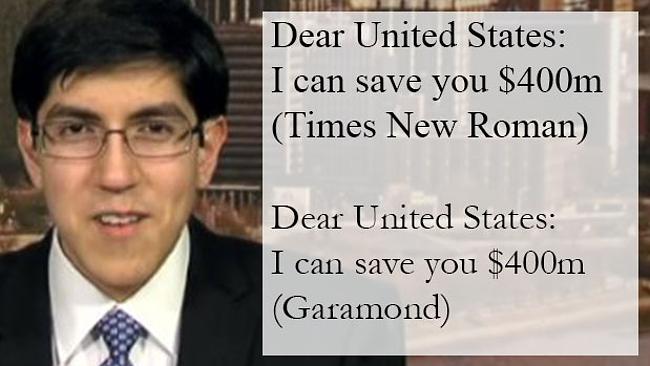
Cậu bé 14 tuổi từng muốn "đổi font chữ” để tiết kiệm 400 triệu USD cho Mỹ gây chấn động thế giới giờ ra sao?
Năm 2014, thông tin cậu bé Suvir Mirchandani, 14 tuổi muốn hiến kế cho chính phủ Mỹ thay đổi font chữ để giúp tiết kiệm hàng trăm triệu USD tiền in ấn mỗi năm khiến dư luận ở quốc gia này “dậy sóng”.
Theo Suvir Mirchandani, tính theo thể tích, mực còn đắt gấp đôi nước hoa Pháp. Và trên thực tế, sự tính toán này hoàn toàn chính xác. Cụ thể, mỗi ounce (30 ml) nước hoa Chanel No.5 có giá 38 USD, với cùng thể tích đó lượng mực in chạy cho máy Hewlett Packard ở Mỹ có thể có giá lên đến 75 USD.
Cậu bé Suvir Mirchandani
Cậu bé muốn thay đổi font chữ để giúp tiết kiệm tiền in ấn cho Mỹ. (Ảnh: CNN.)
Cậu bé đã sử dụng cả phương pháp vật lý và phần mềm để chứng minh cách dùng font chữ hiện nay tốn mực in khủng khiếp như thế nào.
Cụ thể, Suvir thử nghiệm viết những chữ cái bằng 4 kiểu font chữ Garamond, Times New Roman, Century Gothic và Comic Sans và sau đó sử dụng công cụ APFill® Ink Coverage Software bản thương mại để đo lường lượng mực in. Kết quả cho thấy, nếu sử dụng Garamond, một loại font có nét mảnh mai hơn, thì hàng năm trường học của cậu bé có thể tiết kiệm được 24% lượng mực in, tương đương với số tiền 21.000 USD.
Và nếu font chữ này được sử dụng rộng rãi ở toàn nước Mỹ thì số tiền mực in có thể tiết kiệm lên tới khoảng 400 trăm triệu USD mỗi năm.
Nếu thay đổi font chữ, số tiền mực in có thể tiết kiệm lên tới khoảng 400 trăm triệu USD mỗi năm
Mặc dù rất tiềm năng nhưng người ta không thể áp dụng nó vào thực tế tại thời điểm hiện tại bởi ngoài lợi ích kinh tế nó còn liên quan tới nhiều yếu tố khác nữa. Nhưng đây quả thực là một nghiên cứu đáng biểu dương.